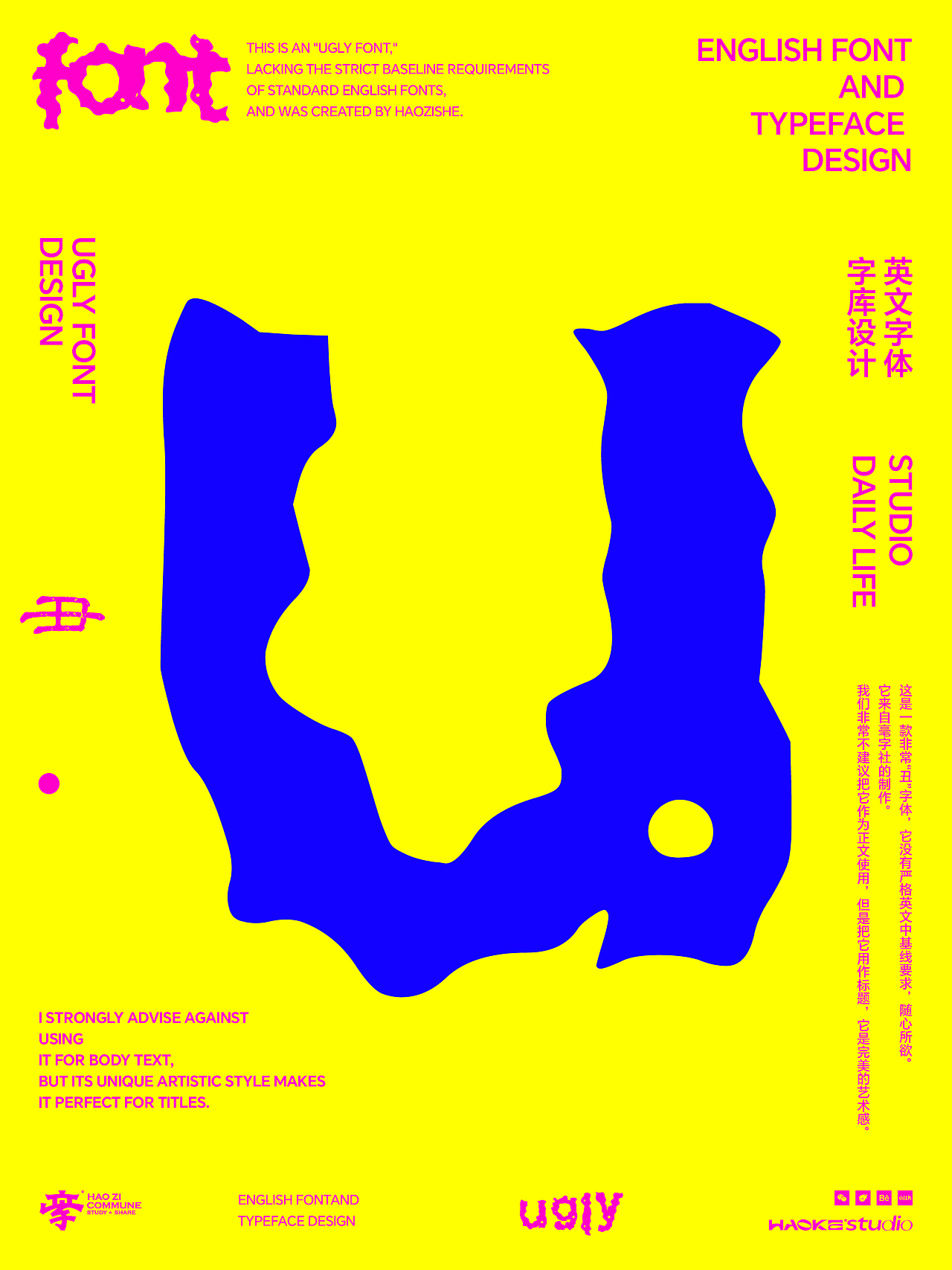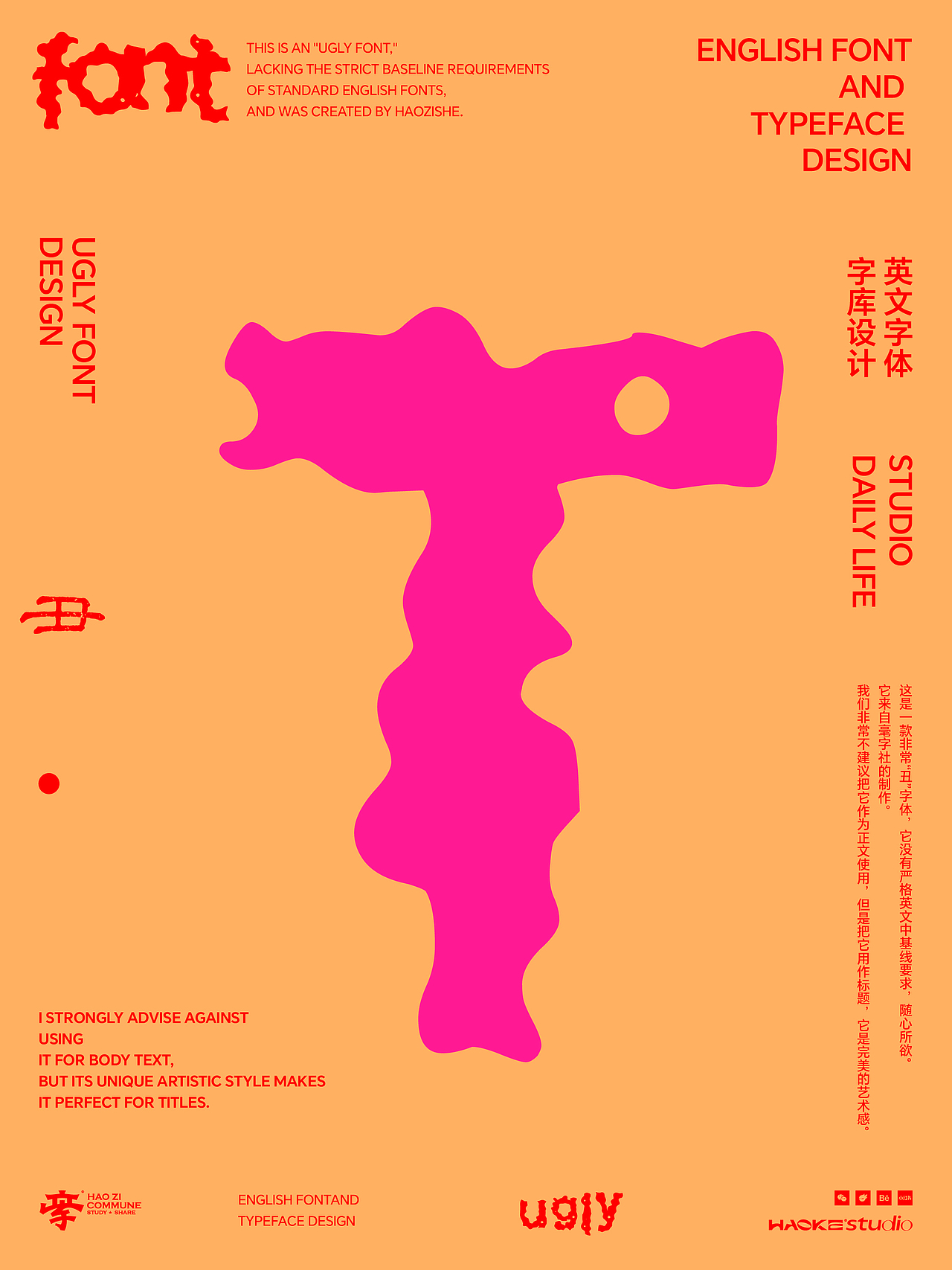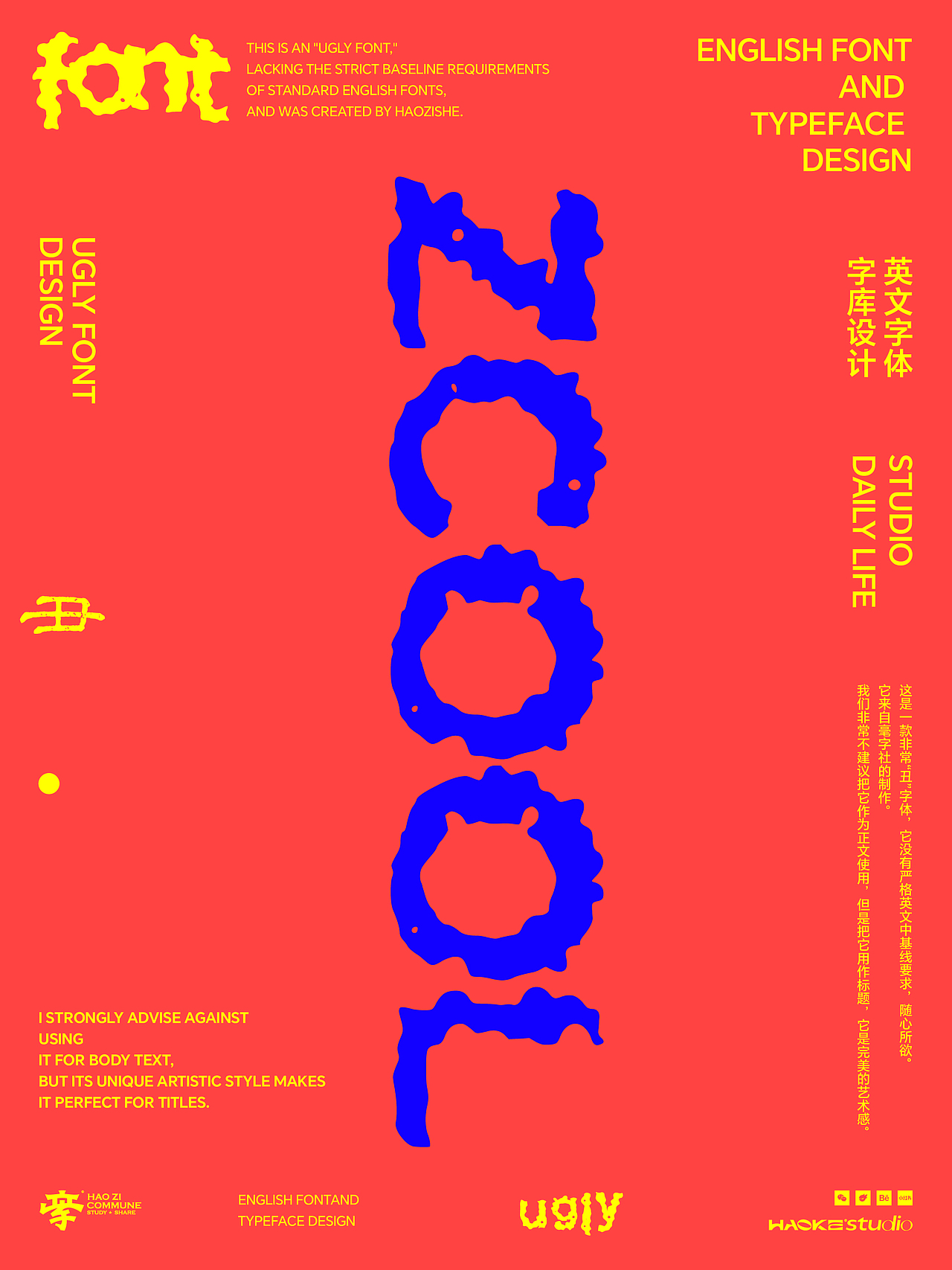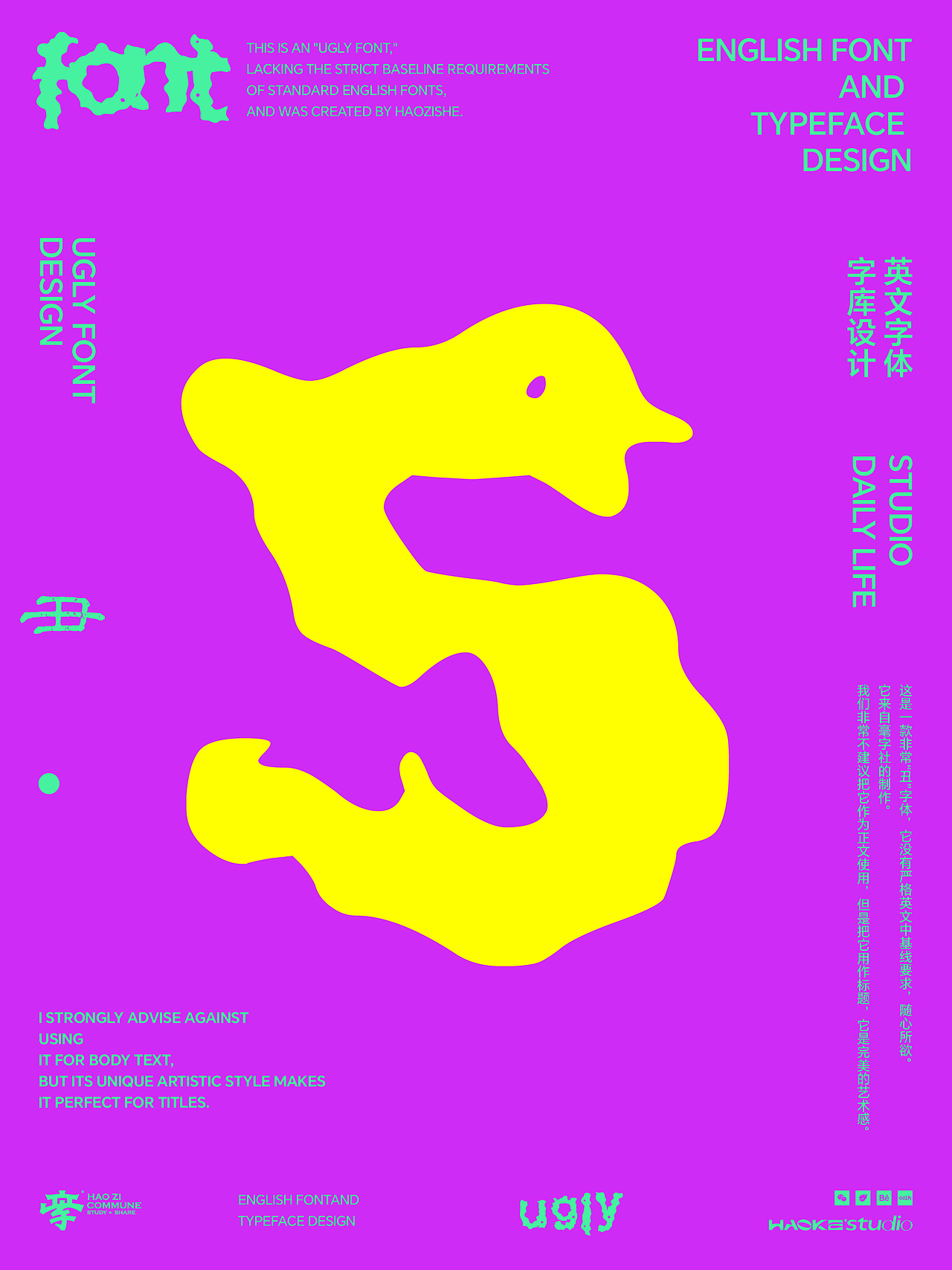
毫字社Ugiy免费商用标题体
Name:Hao Zi She Ugiy Regular
选择设计作为事业是因为专业与热爱,而设计本身则是一种经过深思熟虑的传达。
于是,经过一个多月的努力,我们的首款免费字体“Hao Zi She Ugiy Regular”今天正式发!
美,不该只有一种标准。
在排版设计的世界里,我们习惯了追求绝对的对齐、精准的曲线和严谨的基准线。但生活本身是无序的。
毫字社 Ugiy(Hao Zi She Ugiy Regular)
是一场关于“审丑”的反叛试验。我们故意剥离了传统英文字体的工业美感,保留了手绘时的颤抖、扭曲与不确定性。它不够端庄,甚至有些“丑陋”,但这种不被定义的自由,才是它最强大的生命力。 拒绝平庸的对齐,让每一个字母都成为不安分的灵魂。
天生主角,为标题而生。
如果你在寻找一款能够瞬间抓住眼球、打破沉闷布局的字体,
毫字社 Ugiy
(Hao Zi She Ugiy Regular)
正是你的答案。 它不适合作为静默的说明文字,它生来就是为了呐喊。夸张的块面感和如同有机物般的律动线条,赋予了标题一种雕塑般的艺术感。我们打破了英文字体的固有框架,只为在视觉竞争激烈的时代,为你提供一种极具辨识度的“暴力美学”。
致敬那些“不完美”的灵感
我们建议:
千万别用它排正文,但请务必用它做标题。
这是一款“随心所欲”的字体。 没有基准线,没有标准规范,只有创作者最直觉的表达。 它扭曲、厚重、甚至带着一点怪诞的趣味。 让设计回归直觉,让丑得有个性,成为一种新的流行。
初次见面,这是一份未完待续的“字体礼物”
作为在字库领域的初次尝试,
毫字社 Ugiy标题体
(Hao Zi She Ugiy Regular)
凝结了我们现阶段对视觉艺术的思考。坦诚地说,受限于创作周期,它并非一件完美的工业品,在细节与规范上仍留有遗憾。但我们深知,字体的生命力在于流通与应用。我们坚持将其开放